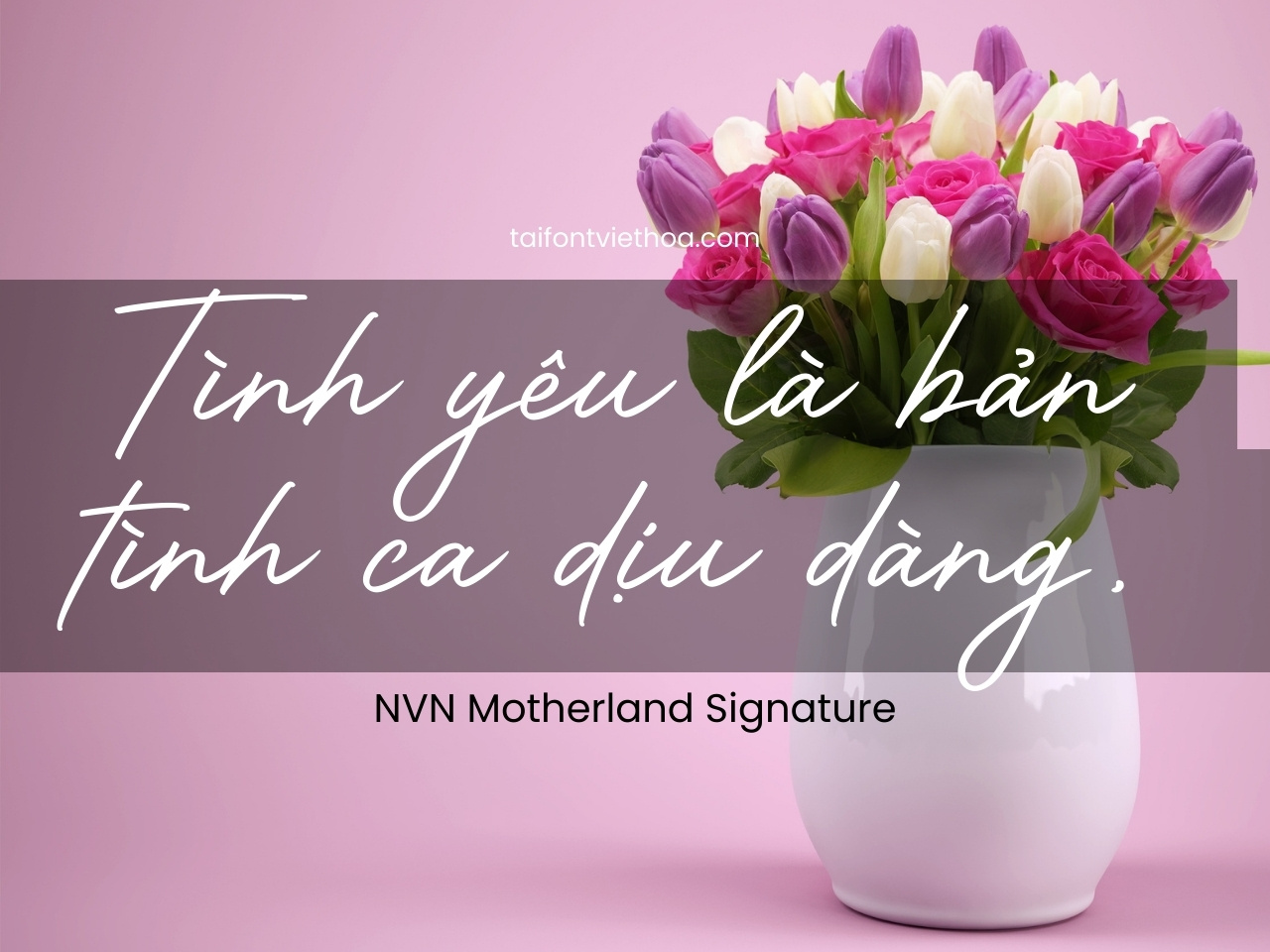
Font việt hóa NVN Motherland Signature
Giới thiệu về font Motherland Signature
Motherland Signature là một font chữ ký (signature script) được thiết kế với phong cách viết tay thanh lịch, nhẹ nhàng và đầy cảm xúc. Font tạo cảm giác cá nhân hóa, giống như một chữ ký thật được viết bằng bút mực. Phiên bản Việt hóa do NVN Font thực hiện, hỗ trợ đầy đủ tiếng Việt với các dấu thanh rõ ràng và mượt mà. Ngoài tiếng Việt, Motherland Signature còn hỗ trợ hơn 40 ngôn ngữ khác nhau dựa trên bảng mã Latin và Latin Extended. Font đã được taifontviethoa.com chọn lọc kỹ lưỡng và thử nghiệm trong nhiều dự án sáng tạo để đảm bảo chất lượng khi sử dụng trong thực tế.
Đặc điểm thiết kế và ứng dụng của Motherland Signature
Font sở hữu các nét chữ mềm mại, thanh mảnh với độ tương phản nhẹ giữa các đường nét. Ligatures được tinh chỉnh kỹ lưỡng nhằm tăng độ liền mạch và tự nhiên khi hiển thị. Motherland Signature mang lại vẻ đẹp sang trọng, nghệ thuật và đầy cá tính, rất lý tưởng cho các thiết kế cần thể hiện cảm xúc hoặc tính cá nhân cao.
Font này phù hợp với các ứng dụng như logo cá nhân, chữ ký thương hiệu, bao bì mỹ phẩm, tiêu đề blog, thiệp cưới và thiệp mời sự kiện cao cấp. Các ngành nghề lý tưởng để ứng dụng font gồm: thiết kế thời trang, mỹ phẩm, tổ chức sự kiện, wedding planner, nhiếp ảnh, spa và thương hiệu sáng tạo dành cho phái nữ.